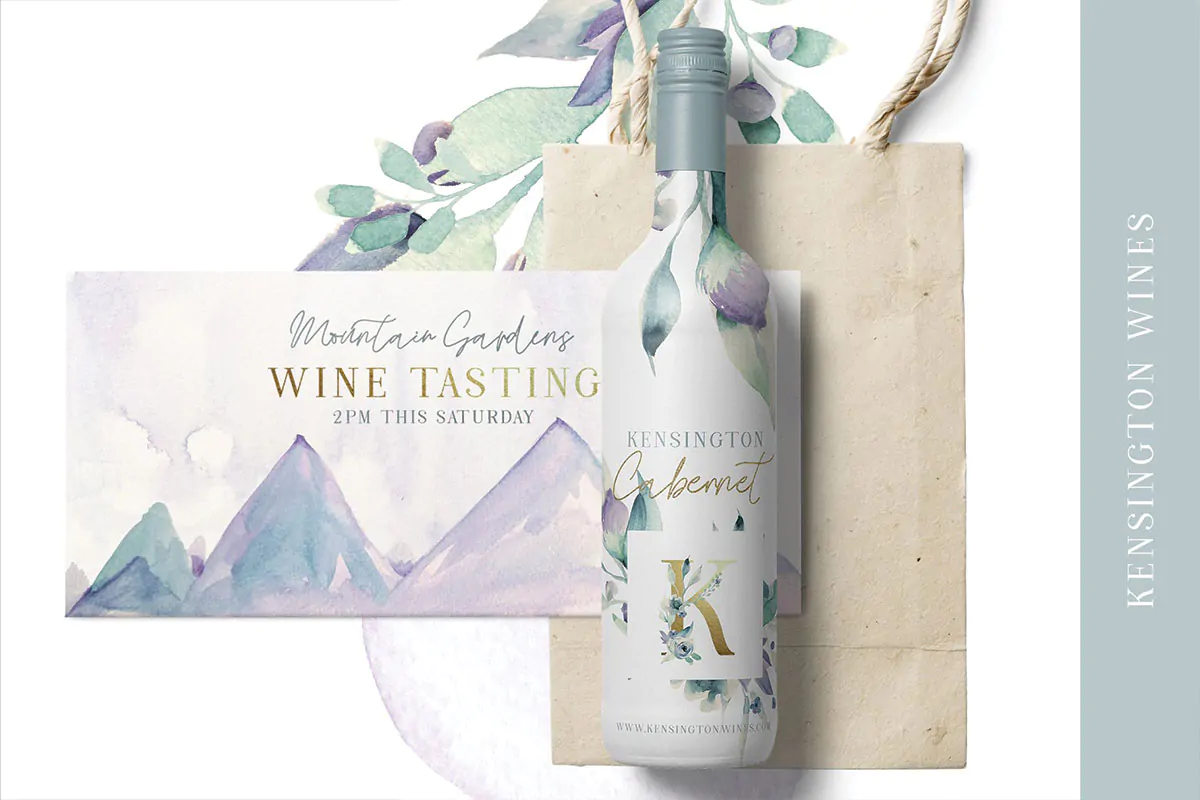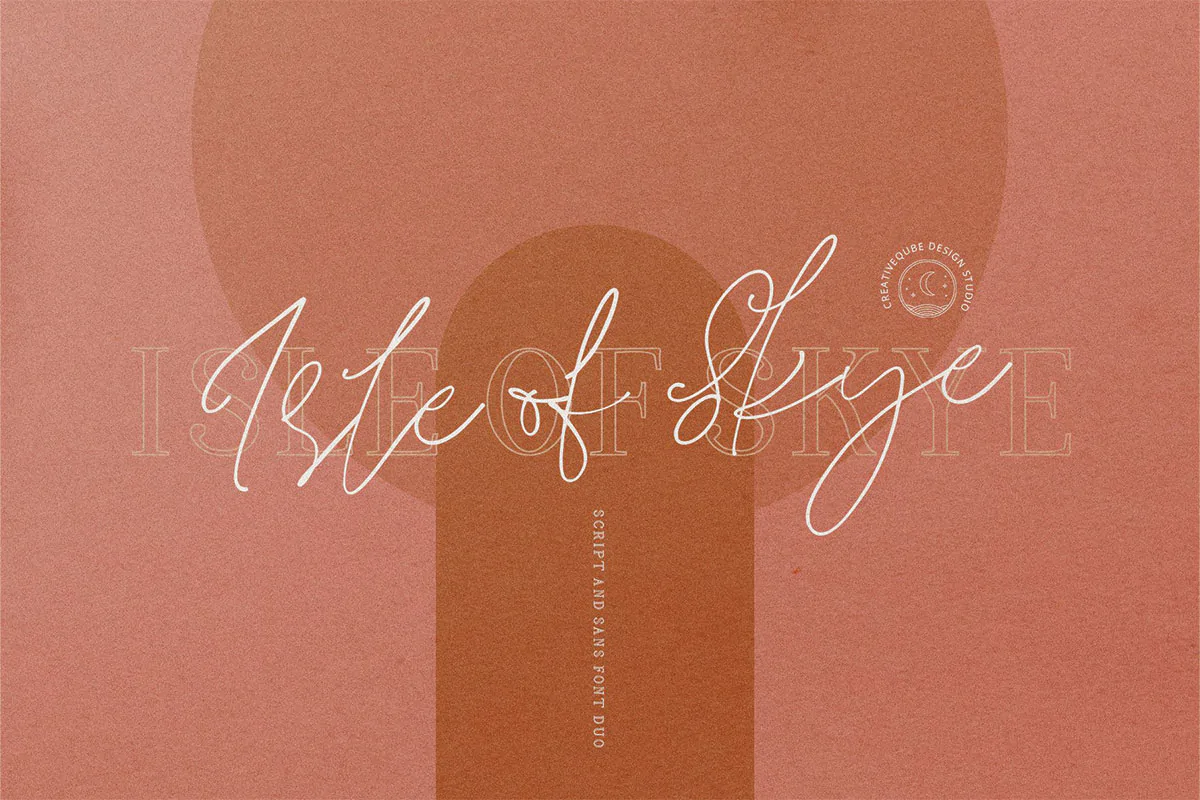
فونت خوشنویسی و سرهم نویسی باریک Isle of Skye
فونت خوشنویسی و سرهم نویسی باریک
فونت خوشنویسی و سرهم نویسی باریک Isle of Skye یک اسکریپت فونت دو تایی فوق العاده زیبا است که با وزنهای مختلف طراحی شده است و مناسب جهت استفاده در طرحهای گرافیکی مختلف از جمله طراحی انواع پوستر، کارت ویزیت، کاور آلبوم موسیقی، رسانههای اجتماعی، کارت تبریک، کارت عروسی، بسته بندی محصولات، آرایشی و بهداشتی و … میباشد.
- Thin، Regular، Italic، Bold، Outline